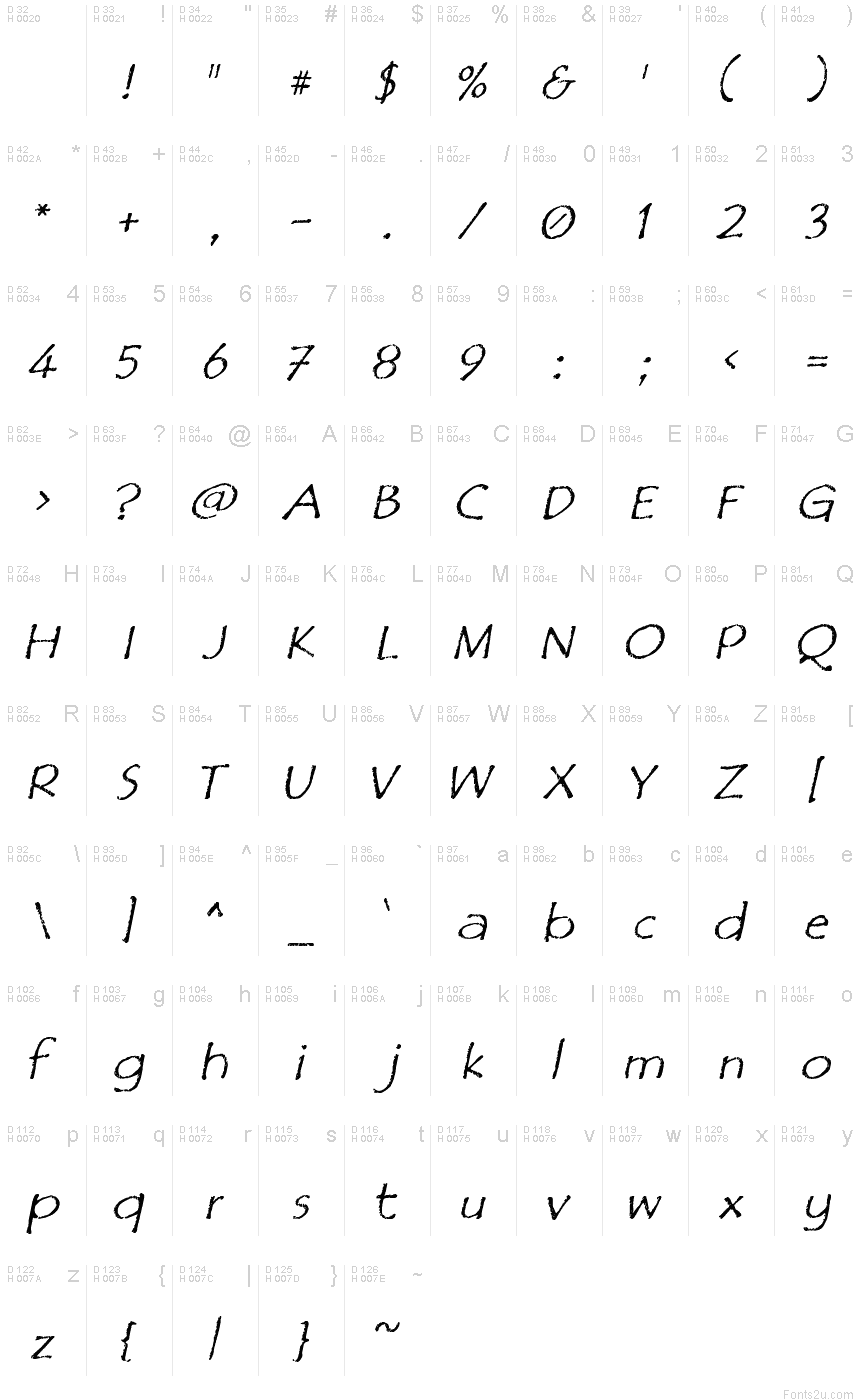
Film Cryptic Oblique
Film Cryptic Oblique autorstwa Grahama Meade’a to darmowy krój pisma odręcznego o poszarpanej, nerwowej energii, która przywodzi na myśl starą taśmę filmową z dreszczowca. Pochylone litery i surowe, zachlapane tuszem krawędzie wyglądają, jakby zostały wydrapane na celuloidzie lub nakreślone w notatniku w migotliwym świetle, nadając Twoim nagłówkom natychmiastowe poczucie niepokoju i pilności.
Film Cryptic Oblique świetnie sprawdzi się w budowaniu napięcia na plakatach horrorów, okładkach thrillerów, grafikach do podcastów kryminalnych, w brandingu escape roomów, na ulotkach zespołów czy w surowych zinach. Luźne odstępy i niespokojne pociągnięcia najlepiej prezentują się w większych rozmiarach, gdzie widać każdą rysę; ten darmowy font warto zestawić z czystym, wąskim krojem bezszeryfowym w tekście pomocniczym, aby Twoje projekty pozostały wyraźne i czytelne.